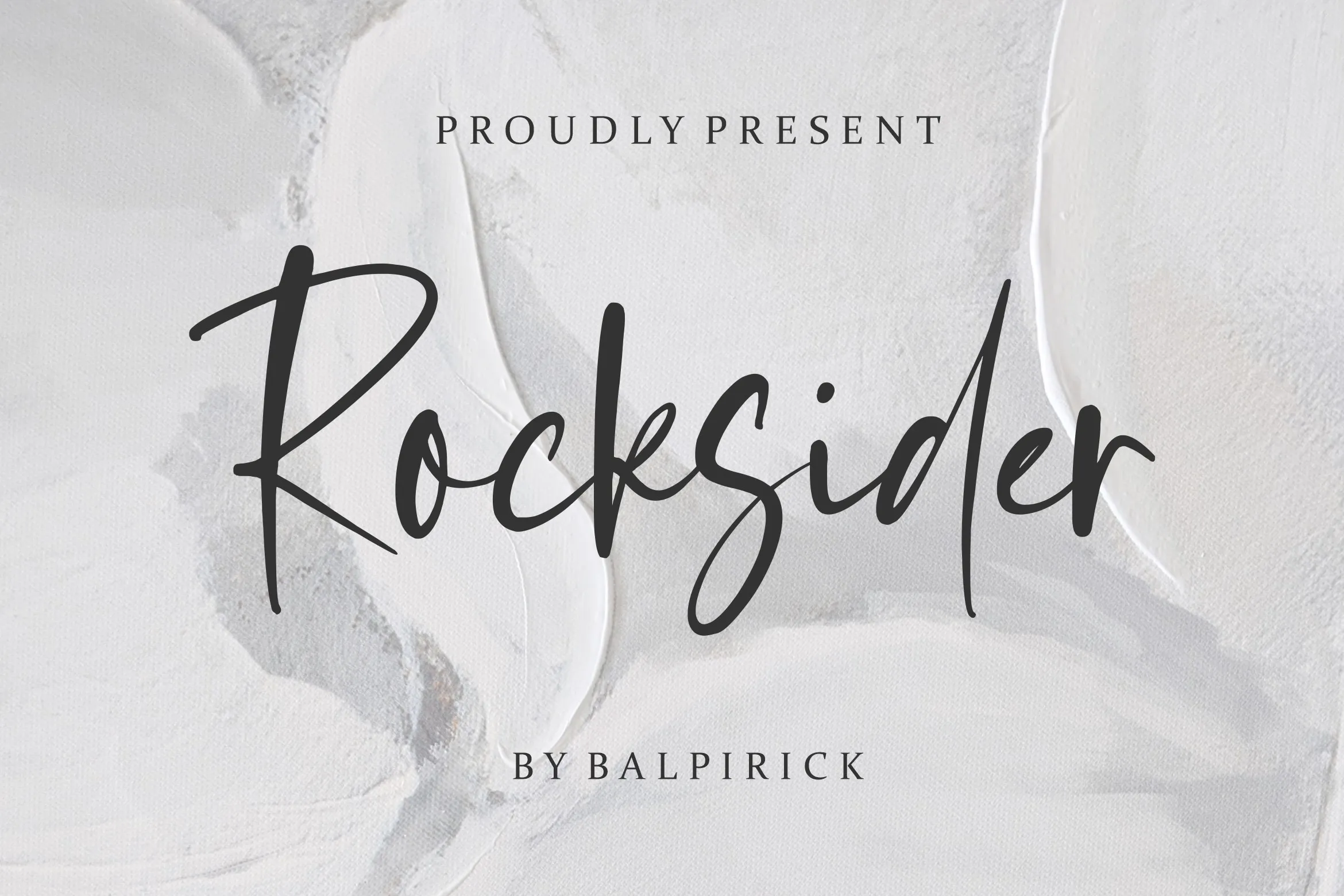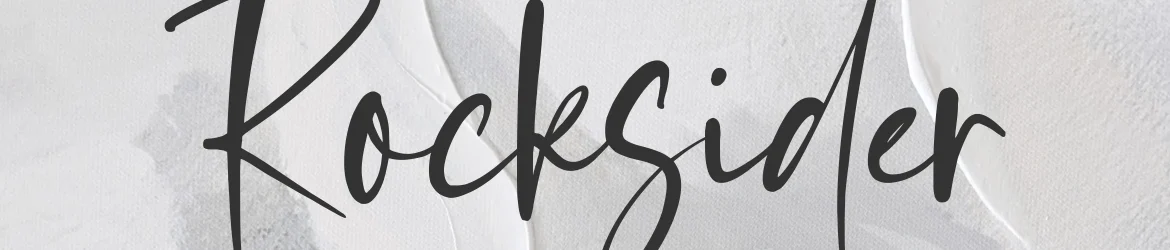
A fonte ‘Rocksider Font’ é uma escolha perfeita para quem busca estilo e casualidade ao mesmo tempo. Ela se destaca como um belo exemplo de tipo à mão escrita, oferecendo um ar elegante e moderno que encaixa-se em uma ampla gama de projetos gráficos. Suas linhas suaves e detalhes sutis dão um toque sofisticado a qualquer design, adequada para criarmos desde identidades visuais e marcas até convites de casamento e postagens nas redes sociais. Seja para expressar sua personalidade no branding pessoal ou em criações publicitárias, ‘Rocksider Font’ oferece uma variedade de opções perfeitas para qualquer projeto que precise de um toque elegante e contemporâneo. É uma fonte ideal para aqueles que valorizam tanto estilo quanto praticidade.